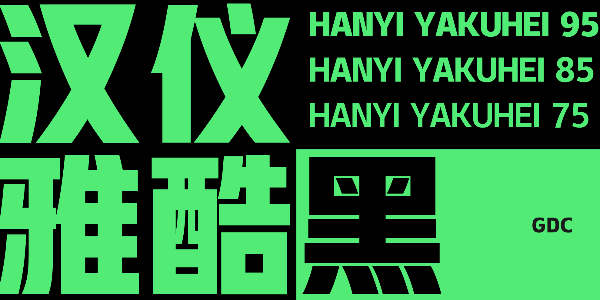
汉仪雅酷黑
汉仪雅酷黑,于2014年获得汉仪字库第一届字体之星设计大赛标题组铜奖,2016年10月完成字库开发并上线,2017年获得了GDC优异奖。在各大热门综艺节目中、无数的电商促销活动中都能见到雅酷黑的身影,历经市场与时间的检验,汉仪雅酷黑拓展成为包含6种字重的家族字体,以满足更为全面的排版需求。
汉仪雅酷黑的整体风格简约大方,雅俗共赏,包容性强,从优雅时尚到潮流酷炫,雅酷黑都可以轻松搞定!
字面大而充实,黑白均衡,块面造型具有视觉冲击力。
略高的视觉重心使字形更为精神、挺拔。
延续了黑体平直的线条构成,在简洁有力的直线中融入克制的弧度,为酷炫的黑体增添一分优雅。
从笔画形态到排布关系,平行的设计语言赋予了这款字体和谐的秩序感,同时让综艺标题字体具有横排笔刷的书写味道。
汉仪雅酷黑的西文部分与中文部分保持一致的风格特征,大写字母偏重于表现棱角分明的酷炫感,小写字母则强调了曲线弧度的优雅感。
汉仪雅酷黑家族包含由粗到细共6种字重,满足从标题到正文的用字需求。汉仪雅酷黑的中宫大小随字重而变化,随着字重的增加,字体稳重的力量感愈加鲜明。
汉仪雅酷黑X家族,以汉仪雅酷黑为基础而拓展创作的造型窄长的家族系列,在x轴方向进行压缩,整体气质更为挺拔利落,以满足更为丰富立体的排版需求。